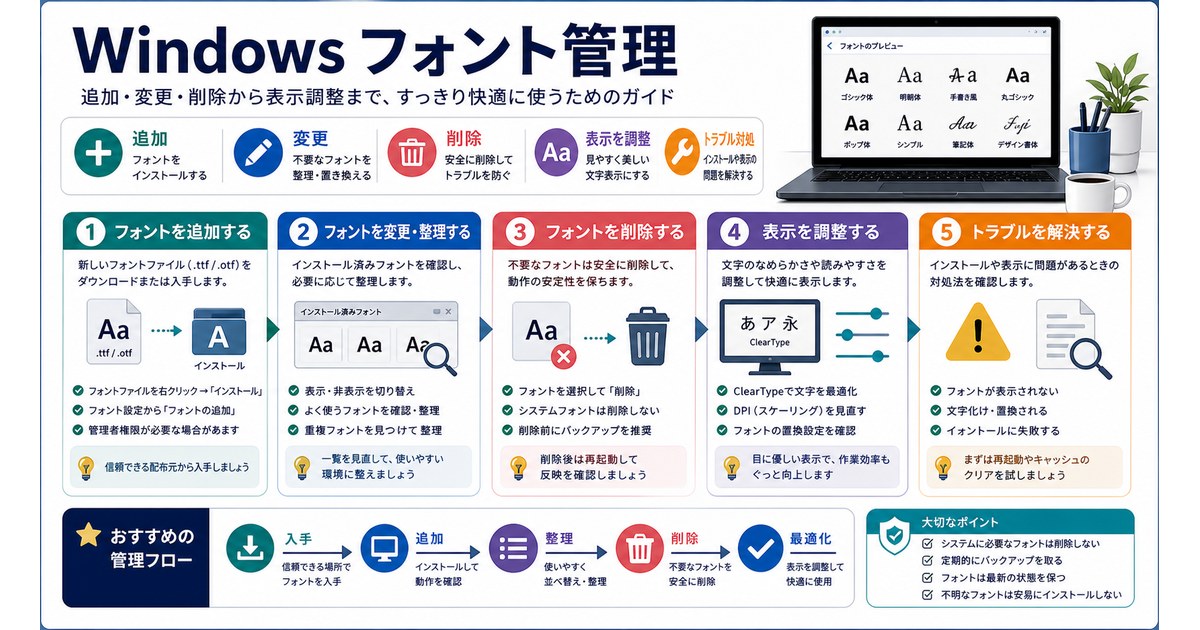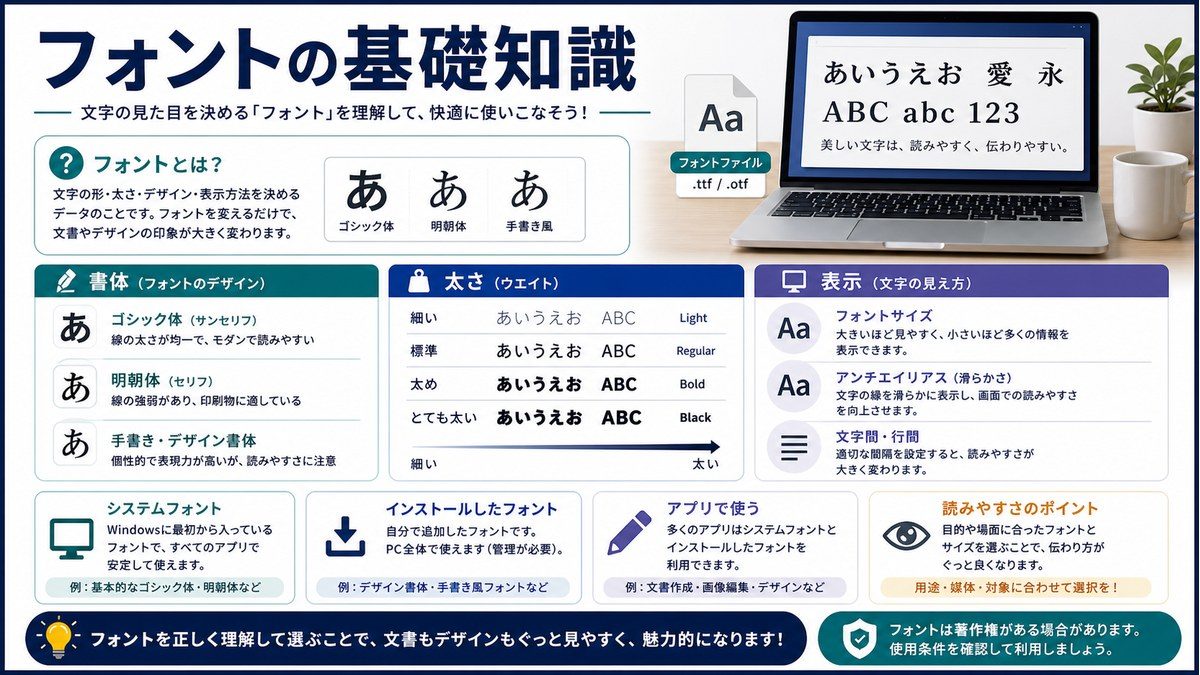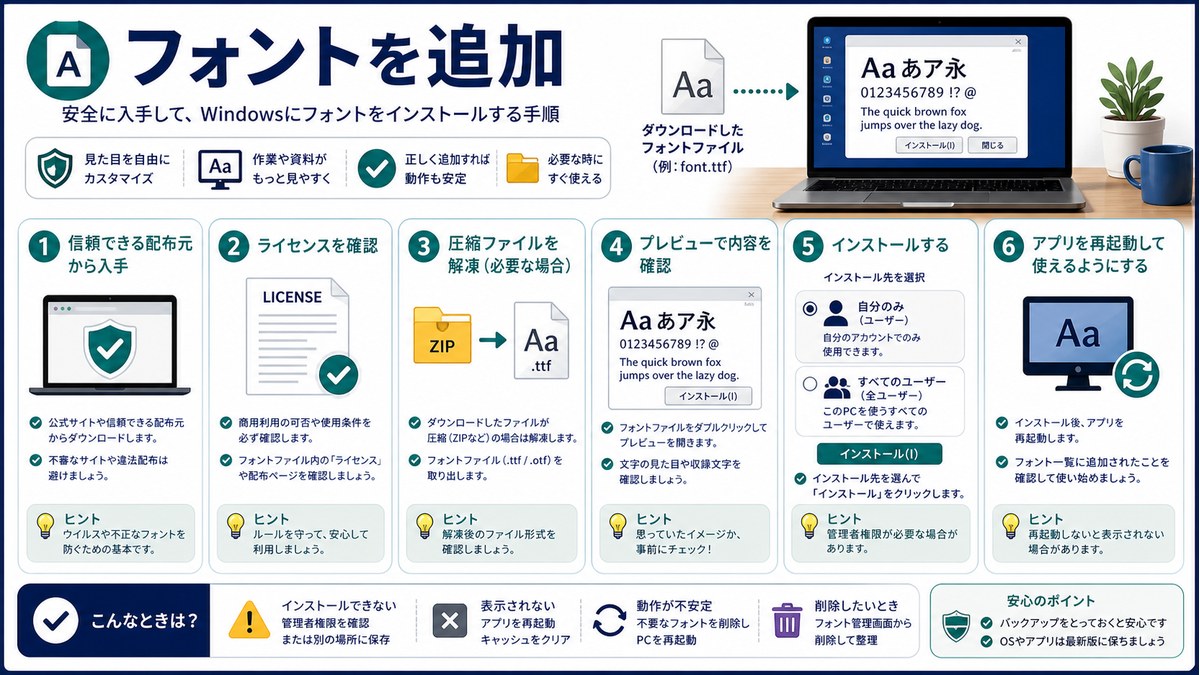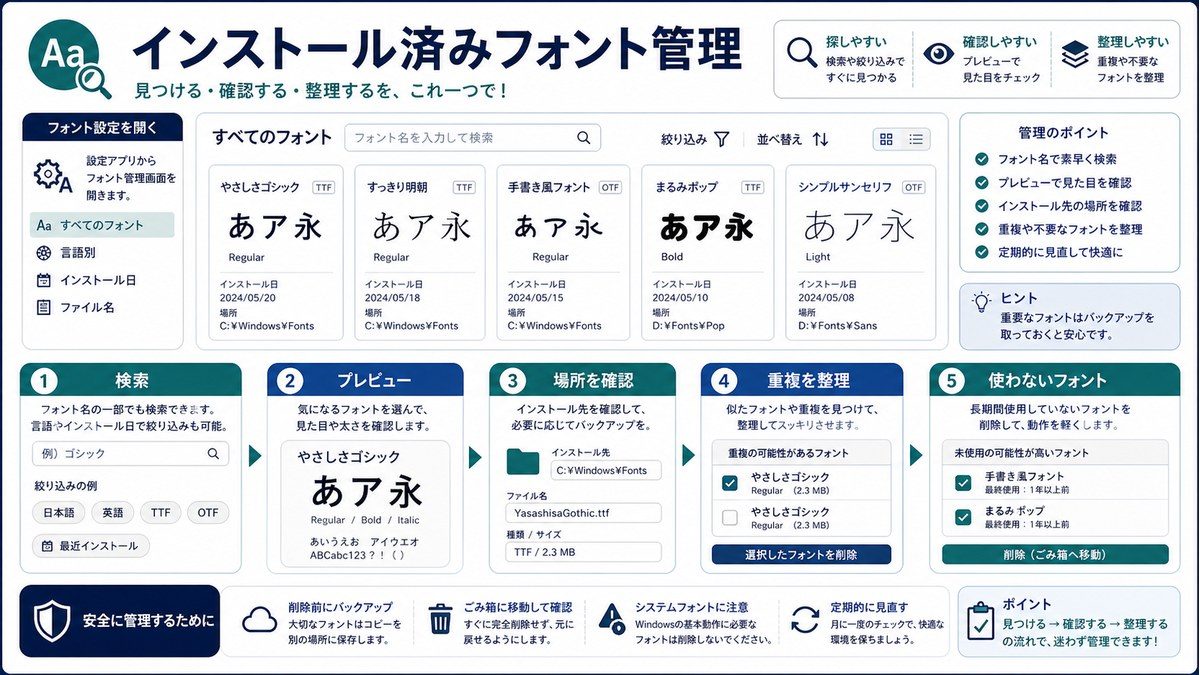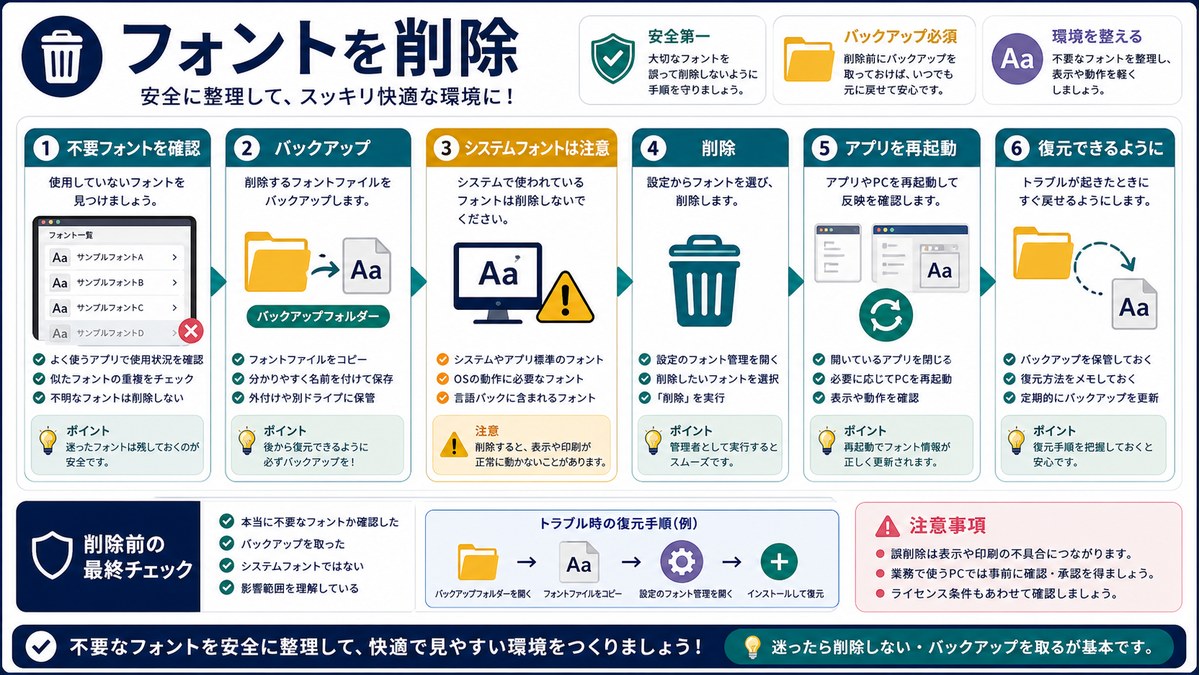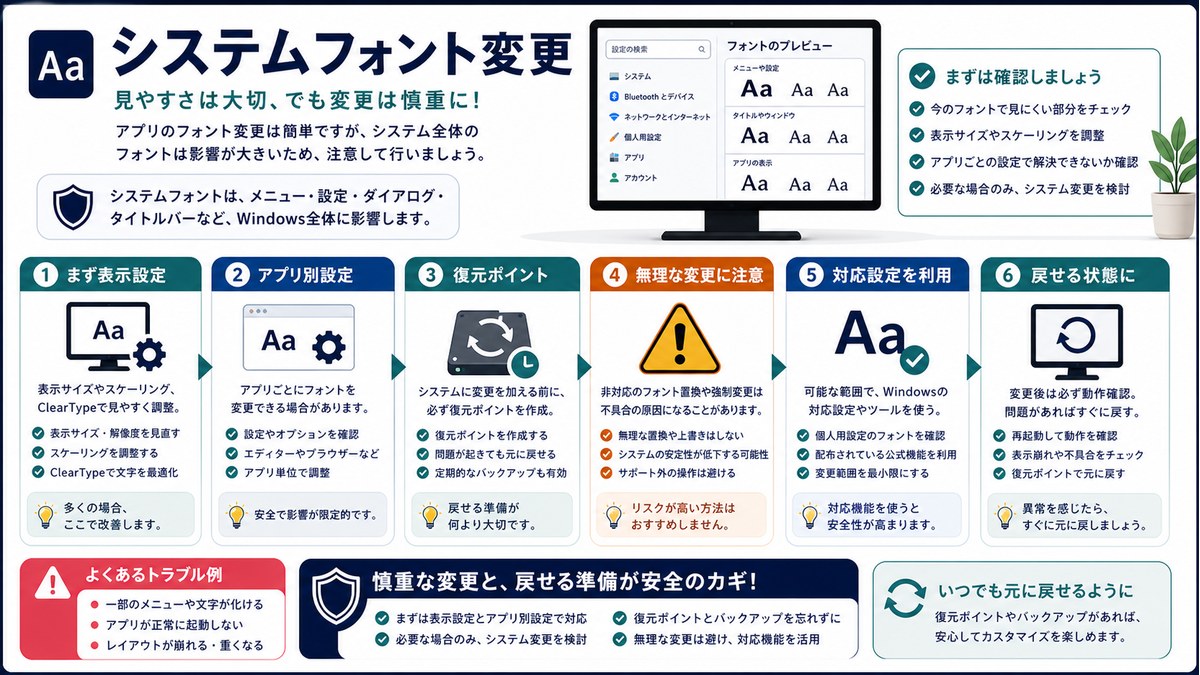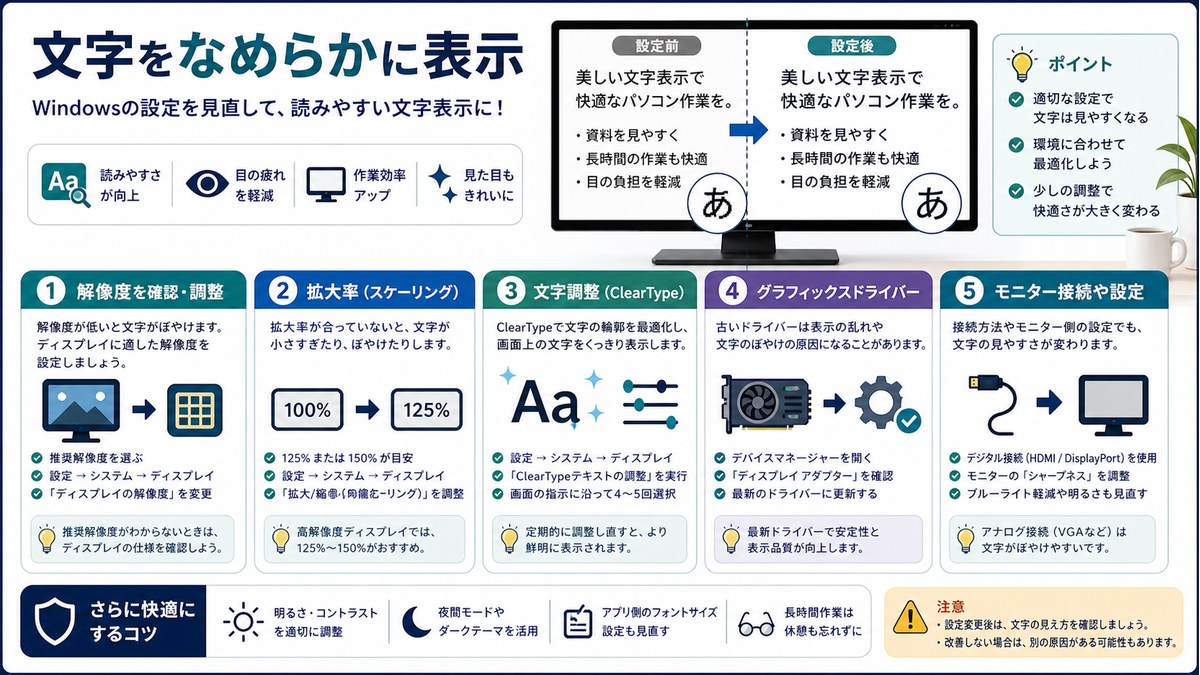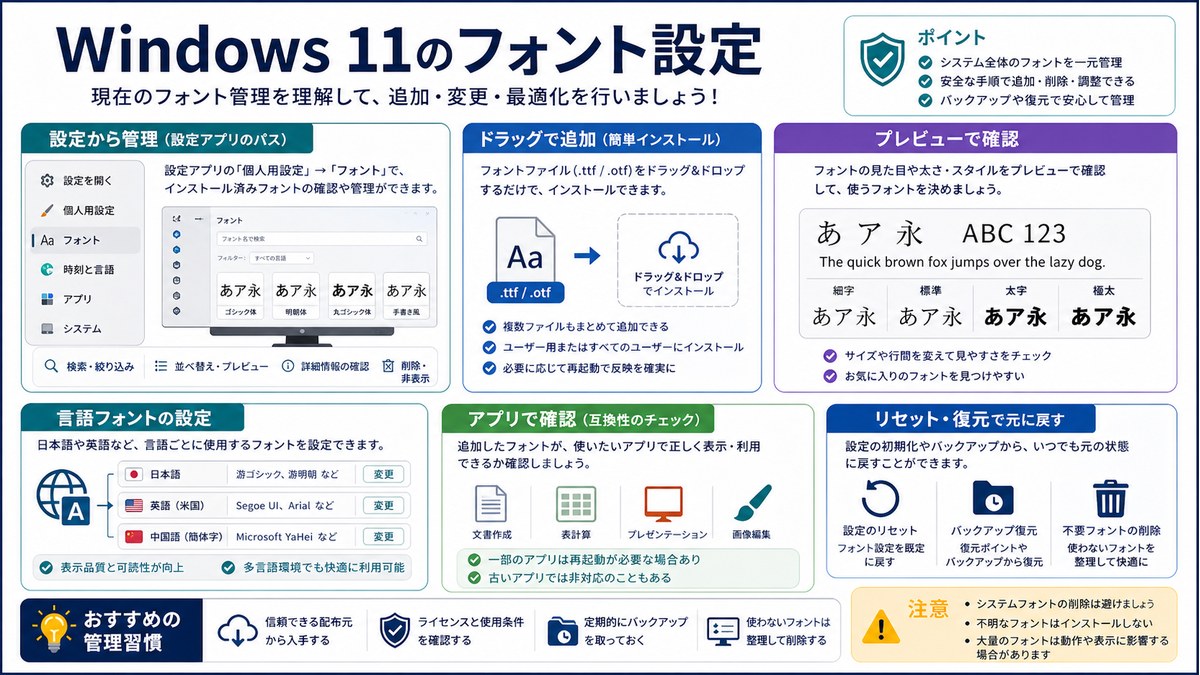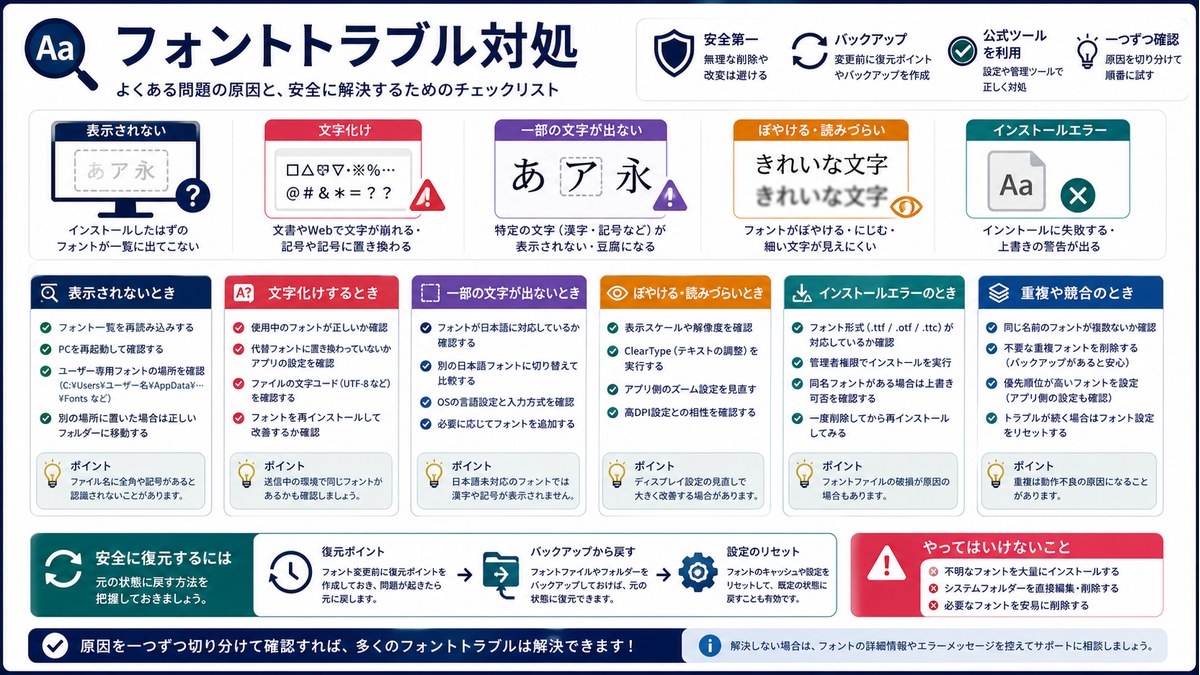
Windowsのフォントを追加・変更・削除する方法【完全ガイド】
【2026年最新版】Windowsのフォントを追加・変更・削除する方法【完全ガイド】
「Windowsの文字がギザギザして見にくい」「もっとおしゃれなフォントを使いたい」「Mac のような滑らかな文字表示にしたい」――そんな悩みを抱えているWindowsユーザーは少なくありません。
フォントはデザインや作業効率に直結する重要な要素です。適切なフォントを選ぶことで、長時間のPC作業における目の疲れを軽減したり、文書の見栄えを大幅に改善したりすることができます。
この記事では、Windows 10 / 11 でフォントを追加・変更・削除する方法を初心者にもわかりやすく解説します。また、Mac風の滑らかなフォント表示を実現するテクニックや、おすすめの無料フォントも紹介します。
この記事でわかること
• Windowsにフォントを追加・インストールする方法(Windows 10 / 11 対応)
• システムフォントを変更してMac風の表示にする方法
• 不要なフォントを削除・無効化する方法
• おすすめの無料日本語フォント5選
• ClearType / フォントスムージングで文字を綺麗に表示する設定
• フォント変更後のトラブルシューティング
Windowsのフォントの基礎知識
フォントとは何か
フォントとは、文字の形(字体)を定義したデータファイルのことです。同じ「あ」という文字でも、フォントによって見た目が全く異なります。
書体、太さ、表示、システムフォント、アプリ利用を整理した図解
フォントは見た目だけでなく、読みやすさやアプリ表示にも関係します。
Windowsで主に使われるフォント形式は以下の3種類です。
Windowsのデフォルトフォント
Windowsのバージョンによって、デフォルトで使用されているシステムフォントが異なります。
Windowsバージョン デフォルトシステムフォント 特徴
Windows XP / Vista MS UI Gothic ビットマップフォント混在。低解像度環境向け
Windows 7 / 8 Meiryo UI ClearType最適化済み。安定した視認性
Windows 10 Yu Gothic UI(游ゴシック UI) 細身でスタイリッシュ。高解像度向きだが低解像度では見にくい場合あり
Windows 11 Segoe UI Variable 可変フォント対応。サイズに応じて字形が最適化される
この方法はMicrosoft公式のストアからインストールするため、安全性が高くおすすめです。
方法4:複数フォントを一括インストール
多数のフォントファイルを一度にインストールしたい場合は以下の手順が効率的です。
1. インストールしたいフォントファイルをすべて選択します(Ctrl + Aで全選択)
2. 選択したファイルを右クリックします
3. 「インストール」または「すべてのユーザーのためにインストール」をクリックします
4. 一括でインストールが実行されます
インストール済みフォントを確認・管理する方法
検索、プレビュー、場所確認、重複整理、不要フォント確認の図解
インストール済みフォントは検索とプレビューで整理できます。
設定画面でフォントを管理する(Windows 10 / 11)
1. スタートメニューから「設定」を開きます
2. 個人用設定」→「フォント」をクリックします
3. インストール済みのフォント一覧が表示されます
4. フォント名をクリックすると詳細情報とプレビューが確認できます
コントロールパネルからフォントを管理する
1. スタートメニューで「コントロールパネル」を検索して開きます
2. デスクトップのカスタマイズ」→「フォント」をクリックします
3. インストール済みフォントの一覧が表示されます
4. フォントをダブルクリックするとプレビューが確認できます
Windowsのフォントを削除する方法
不要なフォントを削除すると、アプリケーションのフォントリストがすっきりして使いやすくなります。ただし、システムフォントの削除は行わないよう注意してください。
不要フォント確認、バックアップ、システムフォント注意、削除、復元を整理した図解
削除前にバックアップを取り、システムフォントは慎重に扱います。
設定画面からフォントを削除する(推奨)
1. スタートメニューから「設定」→「個人用設定」→「フォント」を開きます
2. 削除したいフォントをクリックします
3. フォントの詳細ページで「アンインストール」ボタンをクリックします
4. 確認ダイアログが表示されたら「アンインストール」をクリックします
コントロールパネルからフォントを削除する
1. コントロールパネルの「フォント」を開きます
2. 削除したいフォントを右クリックします
3. 削除」を選択します
4. 確認ダイアログで「はい」をクリックします
削除禁止のシステムフォント:Segoe UI、Yu Gothic UI、Meiryo UI、MS Gothic、Arial、Times New Roman などのシステムフォントを削除すると、Windowsの表示が崩れる場合があります。削除するのはサードパーティのフォントのみにしてください。
フォントを削除せず「非表示」にする方法
削除はしたくないが、フォントリストから見えなくしたい場合は「非表示(Hide)」設定が便利です。
1. コントロールパネルの「フォント」を開きます
2. 非表示にしたいフォントを右クリックします
3. 表示/非表示」を選択します
4. フォント名がグレー表示になり、アプリのフォントリストに表示されなくなります
システムフォントを変更する方法(Windows 10 / 11)
Windowsのシステム全体で使用するフォントを変更することで、デスクトップや各アプリの文字表示をカスタマイズできます。
表示設定、アプリ別設定、復元ポイント、無理な変更への注意を示した図解
システム全体のフォント変更は戻せる状態を作ってから行います。
重要:Windows 10 バージョン1903以降、設定画面からシステムフォントを直接変更する機能は削除されました。レジストリ編集またはサードパーティツールを使用する必要があります。作業前に必ずバックアップをとることをおすすめします。
方法1:レジストリエディターで変更する(上級者向け)
レジストリを直接編集してシステムフォントを変更する方法です。
1. Windowsキー + R を押して「ファイル名を指定して実行」を開きます
2. regedit と入力してEnterキーを押します
3. レジストリエディターが開いたら、以下のパスに移動します:
HKEY_LOCAL_MACHINE\SOFTWARE\Microsoft\Windows NT\CurrentVersion\Fonts
4. 変更したいフォントのエントリをダブルクリックします
5. 値のデータに新しいフォント名(例:NotoSansJP-Regular.otf)を入力します
6. PCを再起動して変更を適用します
方法2:「Meiryo UI も大っきらい!!」ツールを使う(推奨)
「Meiryo UI も大っきらい!!」は、システムフォントをGUIで簡単に変更できる無料ツールです。レジストリ編集の知識がなくても安全にフォント変更ができます。
1. 配布サイトから「Meiryo UI も大っきらい!!」(noMeiryoUI)をダウンロードします
2. ダウンロードしたzipファイルを解凍します
3. noMeiryoUI.exe を管理者として実行します
4. 変更したいフォント項目(メッセージフォント、ウィンドウタイトルフォントなど)の「選択」ボタンをクリックします
5. 使用したいフォントと太さを選択します
6. 「一括設定」ボタンを押して「設定」をクリックします
7. 「サインアウトして反映する」または「今すぐ再起動する」を選択します
Mac風の滑らかなフォント表示にする方法
Macのフォント表示が綺麗に見える理由のひとつは、アンチエイリアス処理(文字の輪郭を滑らかにする技術)の質の高さです。Windowsでも以下の方法で文字表示を改善できます。
解像度、拡大率、文字調整、ドライバー、モニター接続を確認する図解
文字が汚く見える時はフォントだけでなく表示設定も確認します。
ClearTypeを有効化・最適化する
ClearTypeはMicrosoftのフォントスムージング技術で、LCDモニターでの文字表示を綺麗にします。
1. スタートメニューで「ClearType」と検索します
2. ClearTypeテキストの調整」をクリックします
3. 「ClearTypeを有効にする」にチェックを入れます
4. 「次へ」をクリックして、表示されるサンプルの中から最も見やすいものを選択します
5. 各ステップで好みの表示を選んでいくと、モニターに合わせた最適な設定が完了します
MacTypeを使う(フォント描画の根本改善)
MacTypeはWindowsのフォント描画エンジンを改善するフリーソフトです。インストールするだけで、あらゆるアプリケーションの文字表示がMacに近い滑らかな表示になります。
項目 内容
配布元 GitHub(MacType公式リポジトリ)
対応OS Windows 7 / 8 / 10 / 11(32ビット・64ビット対応)
費用 無料
注意点 一部のアプリで表示崩れが発生する場合あり
MacTypeのインストール手順:
1. GitHubのMacType公式ページからインストーラーをダウンロードします
2. インストーラーを起動し、言語設定を「日本語」に設定します
3. セットアップタイプは「標準」を選択します
4. 起動モードを選択します。通常は「サービスモード」(OS起動時に自動起動)がおすすめです
5. 表示サンプルからお好みのプリセットを選択します(後から変更可能)
6. インストール完了後、PCを再起動します
MacTypeの起動モード比較:
起動モード 特徴 おすすめ対象
サービスモード Windowsサービスとして動作。OS起動時に自動起動。最も安定 常時使用したい方
MacTrayロード タスクトレイから管理。適用するプロセスを選択可能 細かく制御したい方
スタンドアロン 手動で起動・停止が可能。試用に最適 まず試してみたい方
おすすめの無料日本語フォント5選
Mac風の見栄えにしたい方や、より見やすいフォントを探している方におすすめの無料フォントを紹介します。
フォント名 特徴 配布元 ライセンス
Noto Sans JP Google・Adobe共同開発。Macのヒラギノ角ゴシックに近い印象。多言語対応 Google Fonts OFL(商用可)
源ノ角ゴシック(Source Han Sans) Adobeが開発。Noto Sans JPと同一フォントファミリー。7ウェイト収録 Adobe GitHub OFL(商用可)
BIZ UDゴシック モリサワ・Windows 11標準収録。ユニバーサルデザイン。読みやすさ重視 Google Fonts / Windows標準 OFL(商用可)
M PLUS 2 可変フォント対応。丸みのあるデザインで親しみやすい印象 Google Fonts OFL(商用可)
IBM Plex Sans JP IBMが開発。スッキリしたモダンデザイン。ビジネス文書向き Google Fonts OFL(商用可)
Noto Sans JPをシステムフォントとして設定する手順
最もMacに近い表示を実現できるNoto Sans JPをシステムフォントとして設定する詳しい手順を解説します。
ステップ1:Noto Sans JPをインストールする
1. Google Fontsのサイト(fonts.google.com)にアクセスします
2. 検索ボックスに「Noto Sans JP」と入力します
3. 「Noto Sans JP」を選択します
4. 「Download family」ボタンをクリックしてzipファイルをダウンロードします
5. ダウンロードしたzipファイルを解凍します
6. 解凍したフォルダ内のフォントファイルをすべて選択します
7. 右クリックして「すべてのユーザーのためにインストール」をクリックします
ステップ2:システムフォントをNoto Sans JPに変更する
1. 「Meiryo UI も大っきらい!!」ツールをダウンロードして起動します
2. すべてのフォント項目(メッセージフォント、メニューフォントなど)の「選択」ボタンをクリックします
3. フォント一覧から「Noto Sans CJK JP」を選択します
4. スタイルは「Regular」または「Bold」を選択します
5. 「一括設定」→「設定」をクリックします
6. PCを再起動して変更を反映させます
Windows 11のフォント設定(最新情報)
Windows 11では、フォント管理に関していくつかの新機能と変更点があります。
設定から管理、ドラッグ追加、プレビュー、言語フォント、アプリ確認の図解
Windows 11では設定画面からフォント管理を確認できます。
Windows 11での変更点
項目 Windows 10 Windows 11
デフォルトフォント Yu Gothic UI Segoe UI Variable(可変フォント)
可変フォントサポート 部分的(Ver.1703以降) 標準対応・最適化済み
フォント設定UI 設定アプリ(個人用設定) 設定アプリ(個人用設定)+改良されたプレビュー
BIZ UDフォント 一部収録 標準収録(BIZ UDゴシック、BIZ UD明朝など)
Windows 11での可変フォント活用
Windows 11で標準採用されたSegoe UI Variableは、表示サイズに応じて字形が自動的に最適化される可変フォントです。小さいサイズでは読みやすい太めの表示に、大きいサイズではスタイリッシュな細めの表示に自動調整されます。
テキストサイズを変更したい場合は次の手順で行えます。
1. 「設定」→「アクセシビリティ」→「テキストサイズ」を開きます
2. スライダーを動かしてテキストサイズを調整します(100%〜225%)
3. 「適用」をクリックします
フォントトラブルシューティング
フォントをインストールしたのにアプリに表示されない
フォントをインストールしてもWordやExcelなどのアプリのフォントリストに表示されない場合の対処法です。
表示されない、文字化け、重複、アプリ再起動、破損確認、復元を整理した図解
フォントが表示されない時はアプリ再起動や破損、重複を順に確認します。
1. アプリケーションを一度完全に終了して再起動します
2. それでも表示されない場合はPCを再起動します
3. 「現在のユーザーのためにインストール」でインストールしたフォントが管理者権限のアプリに表示されない場合は、「すべてのユーザーのためにインストール」でインストールし直します
システムフォント変更後に表示が崩れた
システムフォントを変更後、一部のアプリで文字が正常に表示されなくなった場合は元に戻す手順を実行します。
1. 「Meiryo UI も大っきらい!!」を起動します
2. 「デフォルトに戻す」または「リセット」ボタンをクリックします
3. PCを再起動します
4. Windowsのデフォルトフォントに戻ります
MacTypeをアンインストールする方法
1. スタートメニューから「設定」→「アプリ」→「アプリと機能」を開きます
2. 一覧から「MacType」を見つけてクリックします
3. 「アンインストール」をクリックします
4. アンインストールウィザードに従って完了します
5. PCを再起動するとフォント描画が元の状態に戻ります
フォントファイルが壊れている・インストールできない
フォントファイルが壊れているまたは対応していない形式の場合、インストールに失敗することがあります。
• 配布元の公式サイトから再ダウンロードします
• ダウンロードしたzipファイルが正しく解凍されているか確認します
• .woff / .woff2 形式はWebフォント用のため、Windowsには直接インストールできません。.ttf または .otf 形式を使用してください
🛒
この記事に関連するおすすめ商品
ロジクール ワイヤレスマウス
約3,960円
静音・3台切替
Amazonで探す
※ 価格は変動します。最新価格はリンク先でご確認ください
よくある質問(FAQ)
Q1. フォントのインストール数に上限はありますか?
Windowsには技術的なフォントインストール数の上限があります。Windows 10 / 11ではレジストリの制約により、インストールできるフォントファイルの合計数はおおよそ1,000〜2,000個程度が上限の目安とされています。大量のフォントをインストールしすぎると、アプリケーションの起動が遅くなったり、フォントリストの表示に時間がかかったりする場合があります。必要なフォントだけをインストールするようにしましょう。
Q2. MacのヒラギノフォントをWindowsで使えますか?
ヒラギノフォント(ヒラギノ角ゴシック、ヒラギノ明朝など)はmacOSにライセンスされた商用フォントです。macOSから取り出してWindowsで使用することはライセンス違反になります。代替としては、Noto Sans JPや源ノ角ゴシックなど、ヒラギノに近い見た目の無料フォントをご利用ください。
Q3. システムフォントの変更は安全ですか?
サードパーティのツール(「Meiryo UI も大っきらい!!」など)を使ったシステムフォントの変更は比較的安全ですが、いくつかのリスクがあります。一部のアプリケーションでは選択したフォントに対応していない文字が含まれる場合、文字化けや「□」(豆腐)が表示されることがあります。変更前には必ずシステムの復元ポイントを作成することをおすすめします。
Q4. MacTypeはWindows 11に対応していますか?
MacTypeはWindows 11でも動作しますが、公式には完全な対応を謳っていないバージョンも存在します。GitHub上の最新版を使用することで比較的安定して動作するケースが多いようです。ただしWindows Updateによって挙動が変わる場合もあるため、最新情報をGitHubのIssueページで確認することをおすすめします。
Q5. Google Fontsのフォントをダウンロードして使ってもいいですか?
はい。Google Fontsで配布されているフォントの多くはSIL Open Font License(OFL)で公開されており、個人利用・商用利用ともに無料で使用できます。ただし、フォントによってはライセンス条件が異なる場合もあるため、使用前に各フォントのライセンスを確認することをおすすめします。
Q6. フォントを変更するとプリントにも影響しますか?
システムフォントの変更は画面表示だけでなく、印刷にも影響します。ただし、WordやExcelなどのアプリケーションで個別に設定したフォントはシステムフォントの変更とは独立しているため、文書ファイルのフォントに直接影響することは基本的にありません。
Q7. フォントを変更したら文字が化けた。どうすればいいですか?
文字化けが発生した場合は、インストールしたフォントに日本語文字(ひらがな・カタカナ・漢字)が含まれていない可能性があります。日本語対応フォントに変更するか、元のシステムフォント(Yu Gothic UI またはSegoe UI Variable)に戻してください。
Q8. 会社のPCにフォントをインストールしても問題ないですか?
企業環境のPCにフォントをインストールする際は、IT部門や管理者の許可を取ることをおすすめします。会社のPCにはグループポリシーによって制限が設けられている場合があり、管理者権限なしにはインストールできないケースもあります。また、商用フォントを使用する場合はライセンス契約の内容をご確認ください。
Q9. フォントの種類が多すぎてWordで選ぶのが大変です。整理する方法はありますか?
使用しないフォントは「非表示」に設定することで、WordやExcelのフォントリストから除外できます。コントロールパネルの「フォント」から不要なフォントを右クリックし「表示/非表示」を選択してください。削除せずに非表示にできるため、必要になった時に元に戻すことができます。
Q10. スマートフォン向けサイトを制作する際もWindowsのフォント設定は影響しますか?
Webブラウザで表示するWebサイトのフォントは、WebサイトのCSS設定(font-family)が優先されます。WindowsのシステムフォントはWebサイトの表示に直接影響しませんが、CSSでWebフォントが指定されていない場合のフォールバックフォントとしてシステムフォントが使用されることがあります。
まとめ
Windowsのフォントを追加・変更・削除する方法についてまとめます。
目的 おすすめの方法
フォントを追加したい 右クリック→「インストール」が最も簡単。Microsoft Storeからも取得可能
フォントを削除したい 設定→個人用設定→フォント からアンインストール
システムフォントを変更したい 「Meiryo UI も大っきらい!!」ツールを使う
Mac風の表示にしたい MacType + Noto Sans JPの組み合わせが最も効果的
目に優しい表示にしたい ClearTypeの最適化 + テキストサイズの拡大
フォントリストを整理したい 不要フォントを「非表示」設定にする
Windowsのフォントはちょっとした設定変更で大きく見た目が変わります。毎日使うPCだからこそ、自分にとって読みやすく快適なフォント環境を整えることは作業効率の向上にもつながります。
特に長時間PCを使う方には、ClearTypeの最適化とNoto Sans JPへのシステムフォント変更の組み合わせをおすすめします。Mac風の滑らかな表示にこだわるなら、MacTypeの導入も検討してみてください。
まずは比較的リスクの低いClearTypeの最適化から試してみて、物足りなければシステムフォントの変更やMacTypeの導入へとステップアップしてみるとよいでしょう。